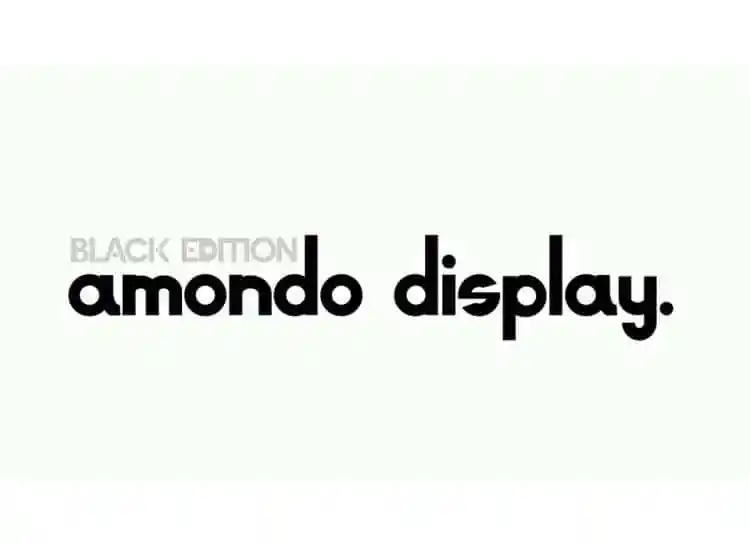
A Mondo Sans Serif Font é uma elegante tipografia moderna inspirada em fontes vintage. Ela foi criada pelo designer font Simon Renoud-Grappin e possui características geométricas fortes que se adaptam perfeitamente a projetos criativos, desde logomarcas e outdoors até letras e identidades de marca. Esta fonte contemporânea é ideal para uma variedade de trabalhos gráficos como o uso em revistas ou outros tipos de arte visual. Com seu design moderno e sua personalidade sólida, esta opção de fonte será perfeita para projetos que exigem estilo e confiabilidade. Que tal explorar suas possibilidades no seu próximo projeto gráfico?